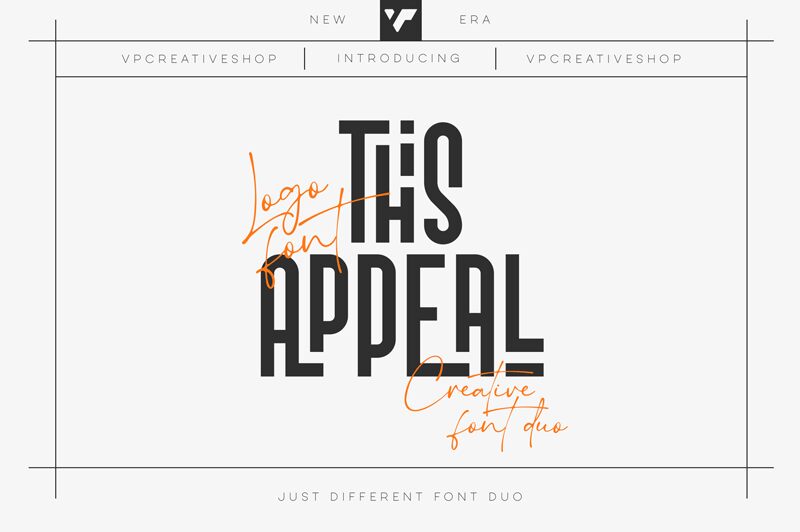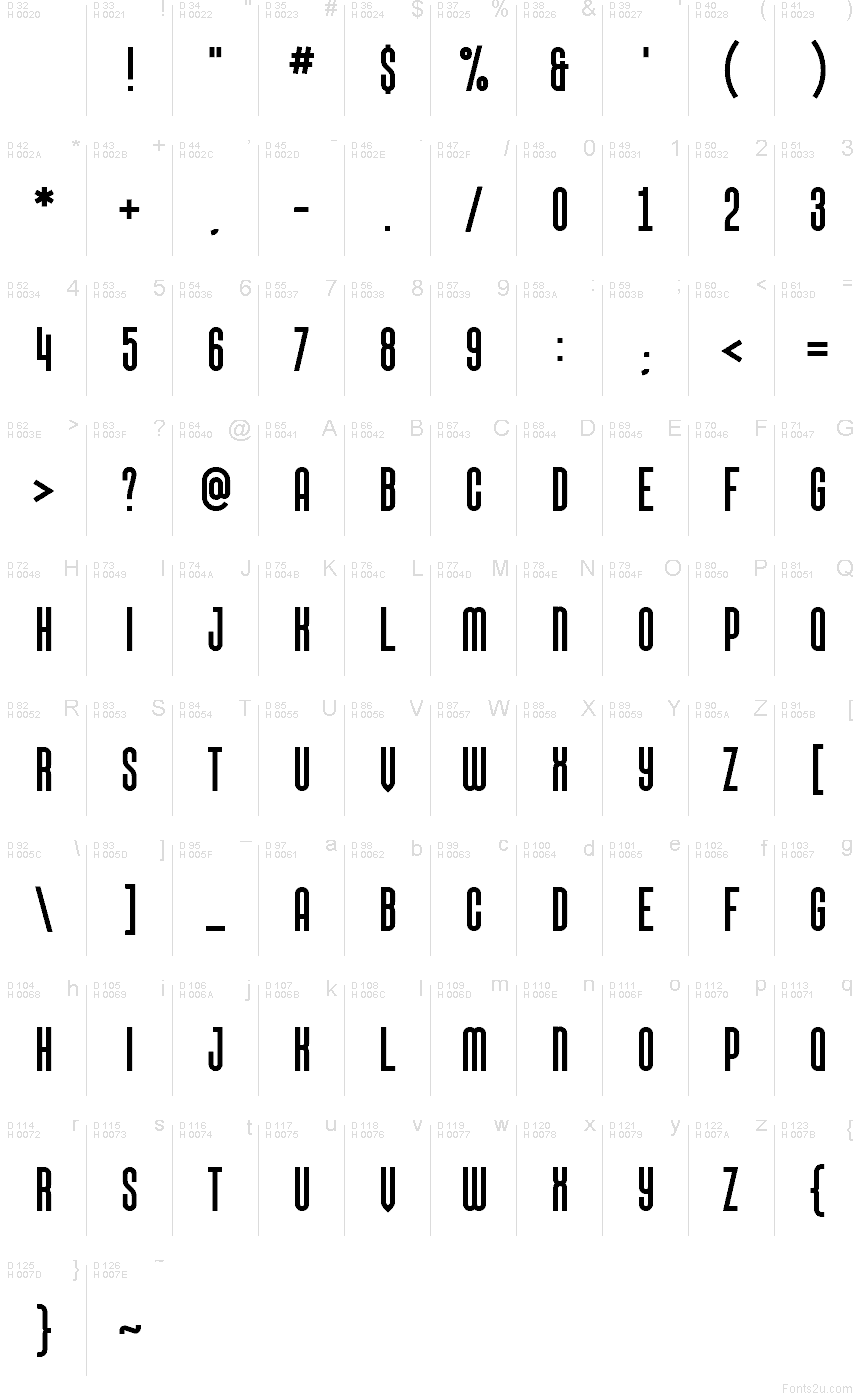
This Appeal Free Demo
Appeal je bezplatné bezpätkové písmo s vysokými, úzko zúženými znakmi a rovnými, minimalistickými ťahmi. Tvary pôsobia štíhlo a vzpriamene, bez zbytočných dekorácií, čo vytvára kompaktný a výrazný rytmus.
Tento bezplatný font Appeal skvele funguje v titulkoch plagátov, na letákoch, obaloch albumov, logách či redakčných nadpisoch, ktoré vyžadujú užší blok textu. Vďaka svojej minimalistickej štruktúre sa hodí aj na branding, obalový dizajn či webové bannery, kde štíhle bezpätkové písmo dokáže upútať pozornosť bez pridania zbytočných ozdôb.